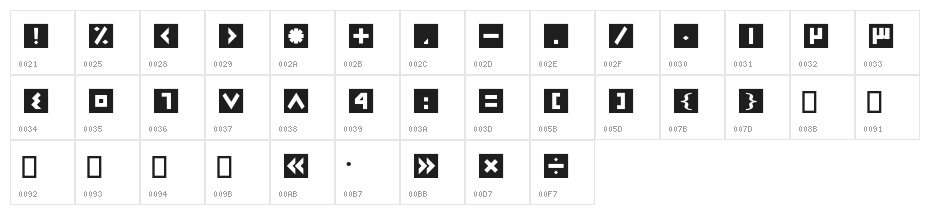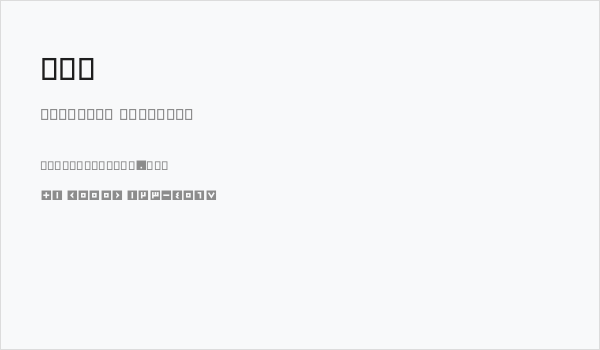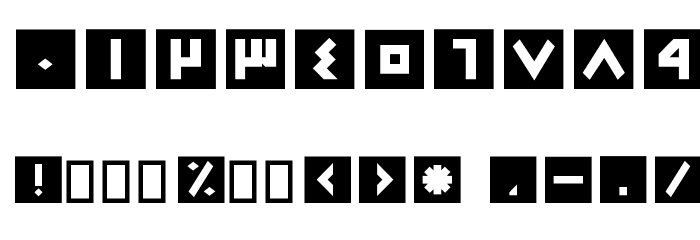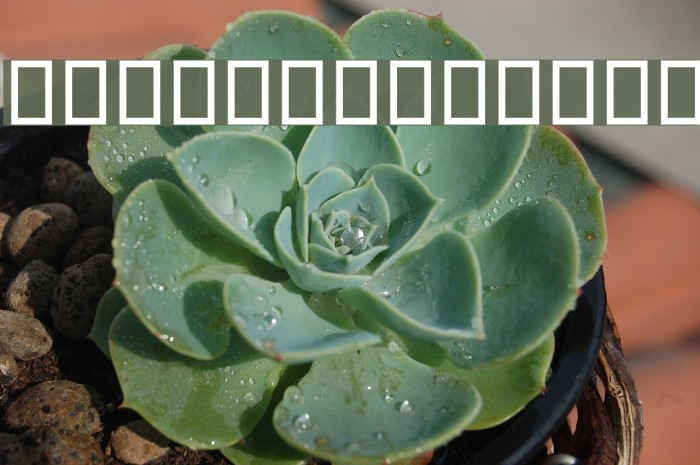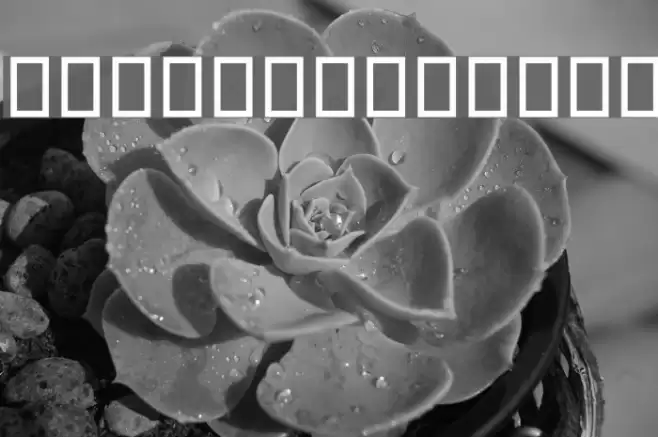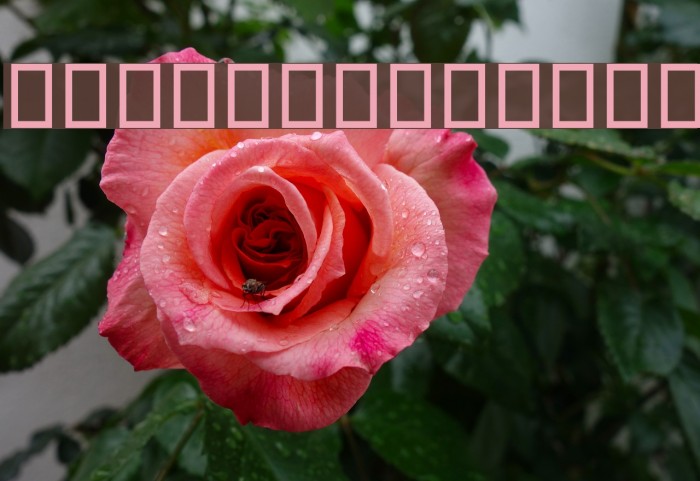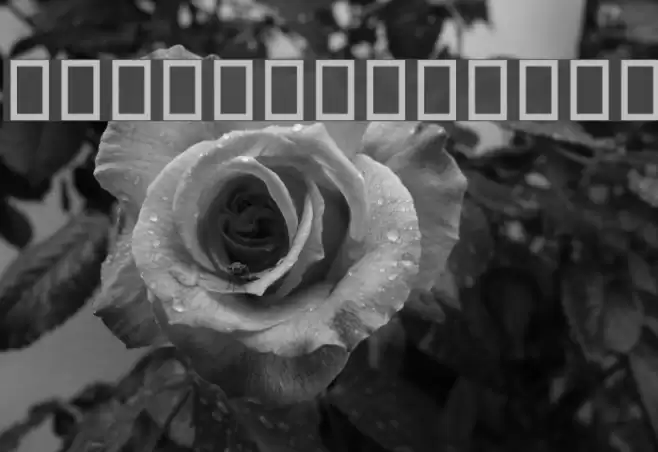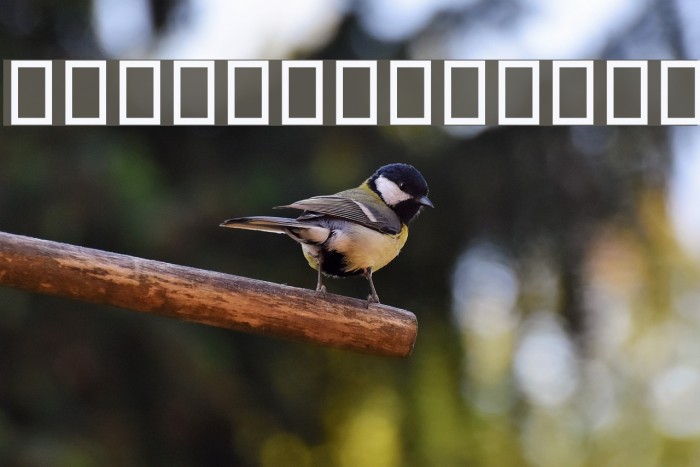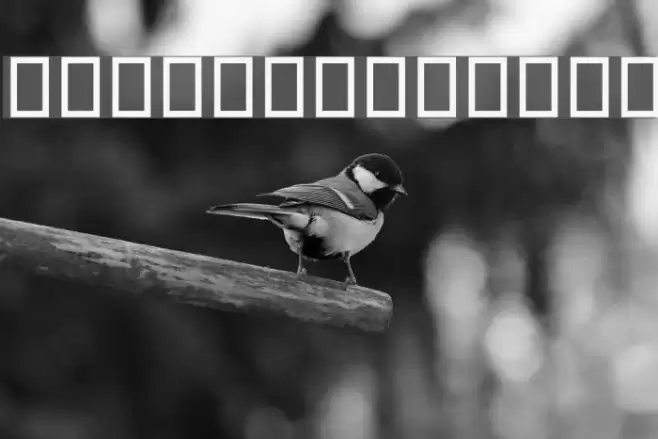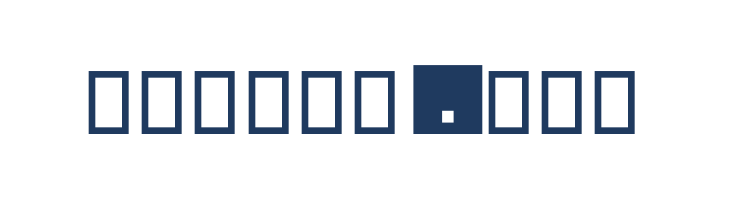
Box Font
| Stil general | Abstract |
| Caz de utilizare | Decorative purposes, placeholders in design. |
| Proiecte propuse | This design could be used for abstract art projects or as a placeholder in design mockups. |